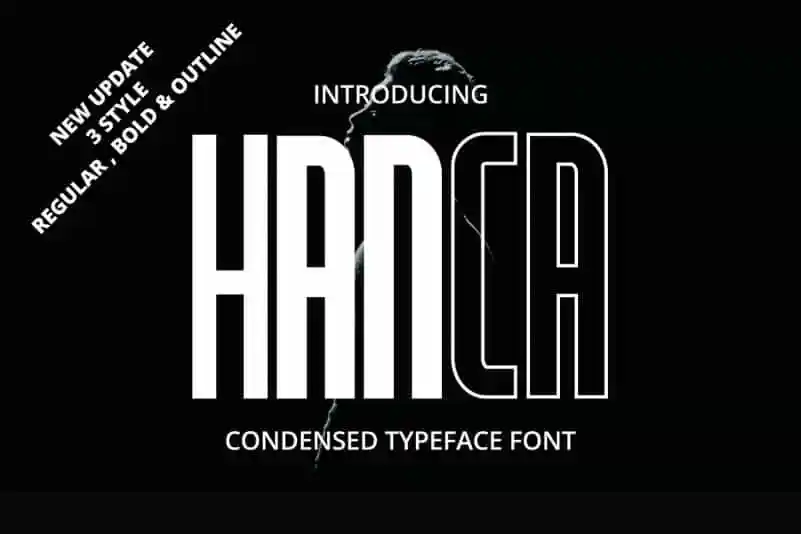
Estamos muito felizes por você verificar a fonte Hanca Display! É uma elegante e poderosa fonte para uso no display, ideal para títulos importantes ou nomes destacados. Construída para maximizar o uso do espaço horizontal, Hanca Display combina um bom equilíbrio entre ser forte e sofisticado. A fonte é projetada e compartilhada pelo VZ Type, e é perfeitamente adequada à aplicação de Hanca Display em diferentes contextos. Esta fonte se destaca como uma opção ideal para headlines em revistas ou portas-duplas, design editorial, materiais impressos, selos de loja, painéis de sinalização, design do vitrine e muito mais. Não perca esta oportunidade de dar um toque distintivo a seus projetos gráficos com Hanca Display!